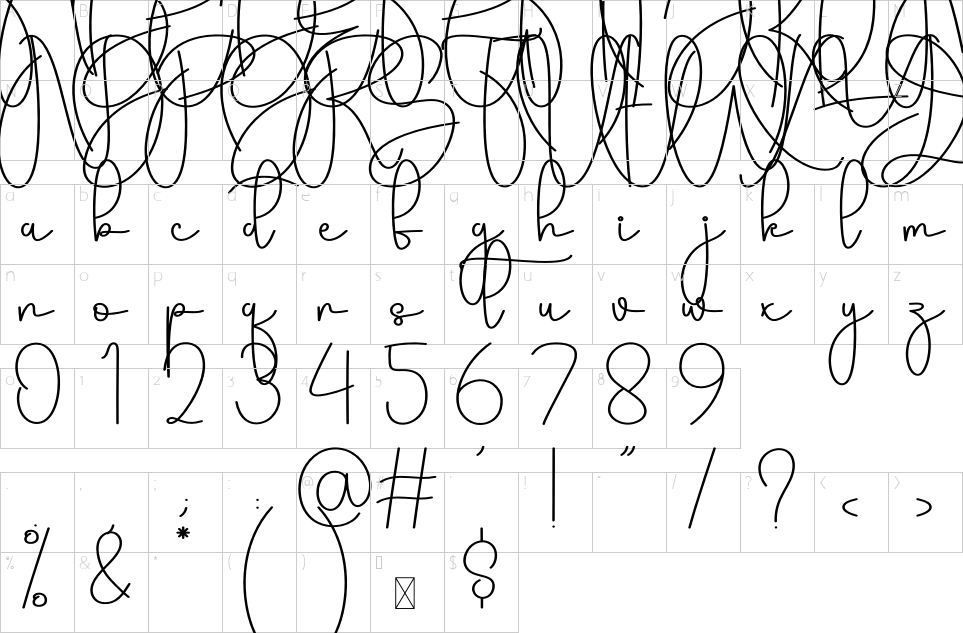
A Motorcycle Font é uma opção gratuita e versátil para quem busca uma fonte interessante para projetos de motocicletas. Desenvolvida por William Jhordy, esta fonte oferece um design único e icônico, adequado para agradáveis aplicativos de design gráfico. Os designers que procuram uma fonte para projetos que incorporam motocicletas, como logotipos ou designs de camisa, vão adorar a Motorcycle Font. Desenvolvida para os sistemas Windows e Mac, a fonte já foi baixada 276 vezes, o que indica seu valor e qualidade. Estamos felizes em oferecer esta fonte gratuita para quem busca uma maneira única de estilizar seus projetos.